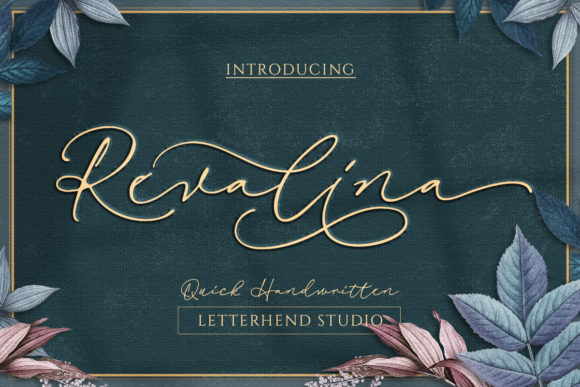
Revalina
Trouver les bons éléments de conception peut être un défi, mais Revalina propose une collection exceptionnelle qui rehausse instantanément votre travail.
Que vous créiez des produits POD (impression à la demande), des invitations de mariage ou des visuels pour les réseaux sociaux, Revalina est un choix idéal.